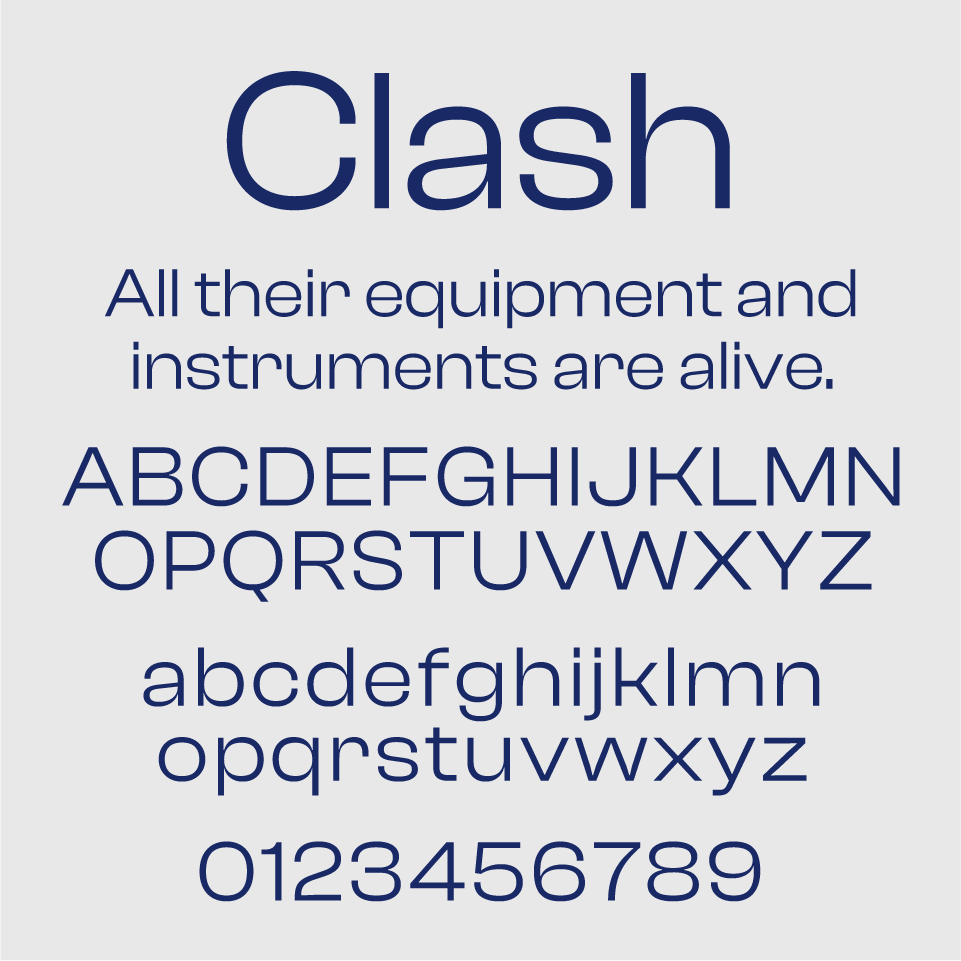
Clash Groteskフォントは、潔くフラットな構造の中に、少しだけひねりのあるディテールが光る、洗練されたサンセリフ体です。角の処理や字幅のバランスが絶妙で、スタイリッシュだけどどこか優しい印象があります。
スッキリとした文字組みが美しく、デジタルにも紙媒体にも自然に馴染みます。まじめすぎず、でもきちんとしている。そんな印象を与えたい場面にぴったりのフォントです。